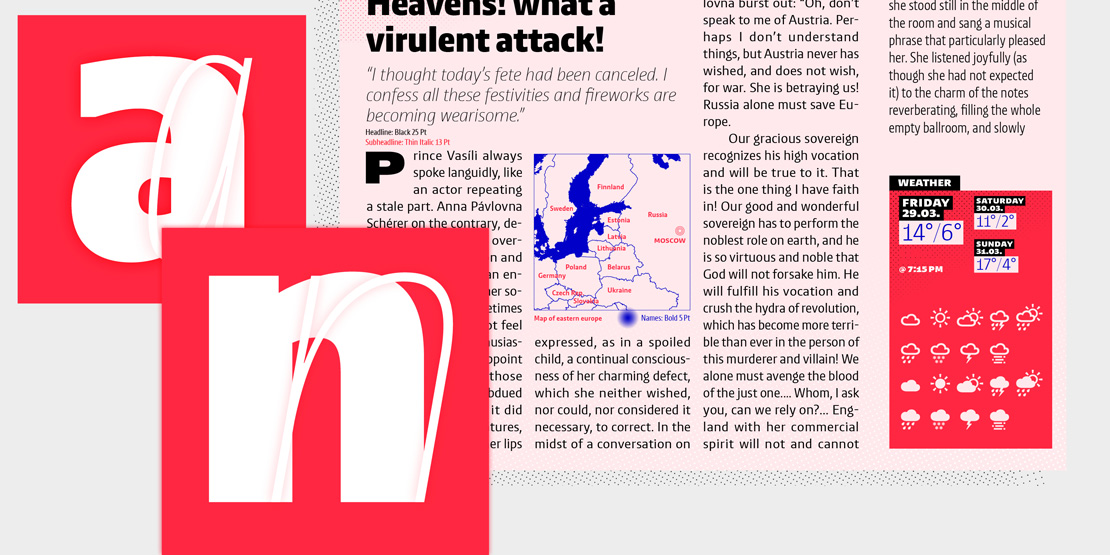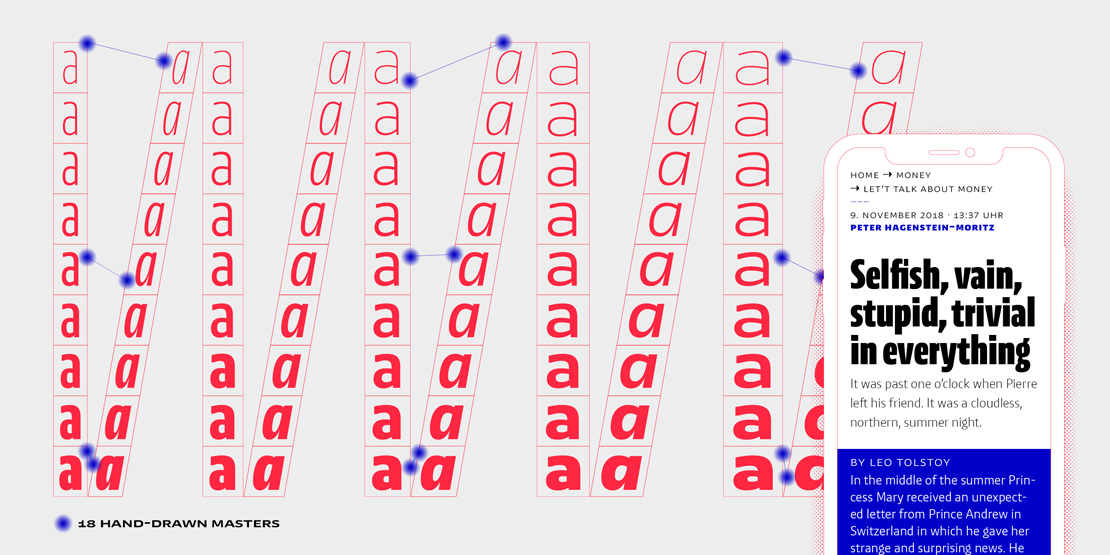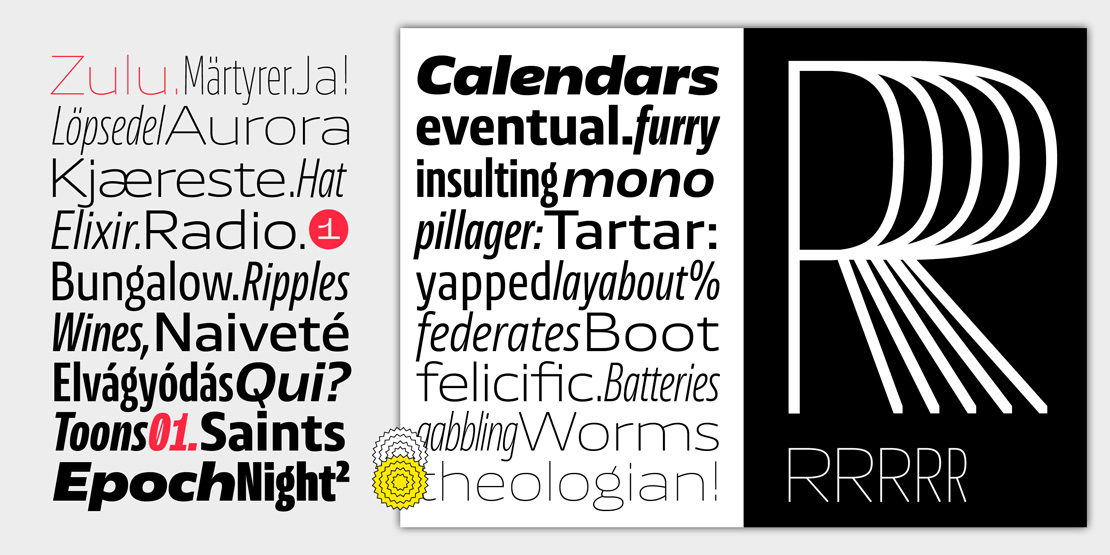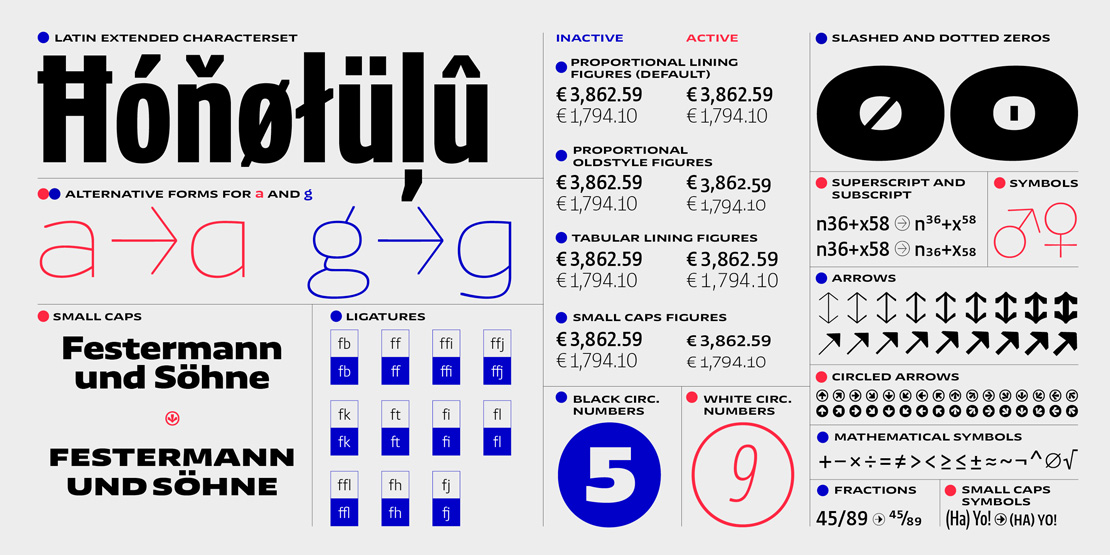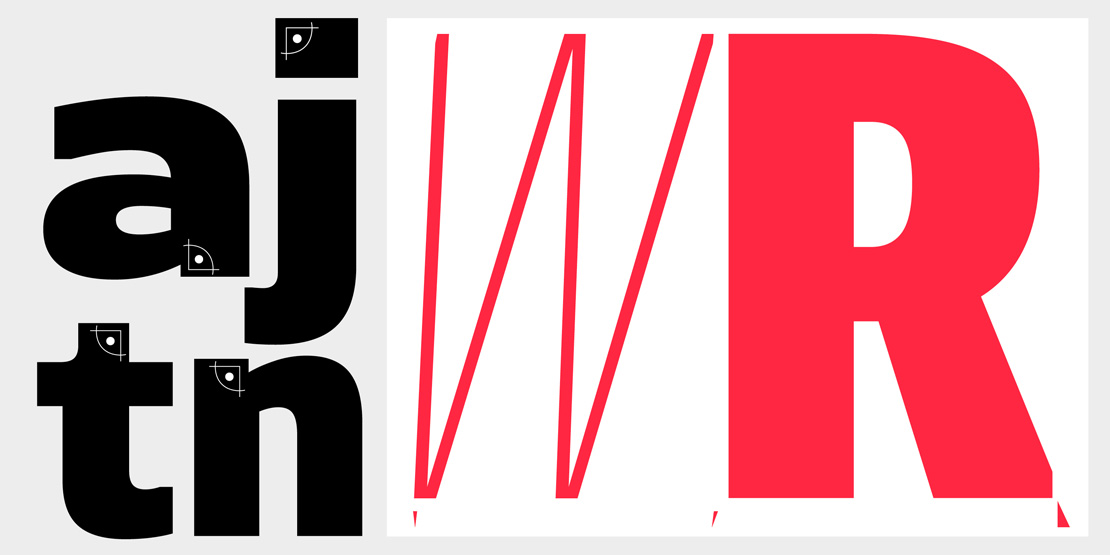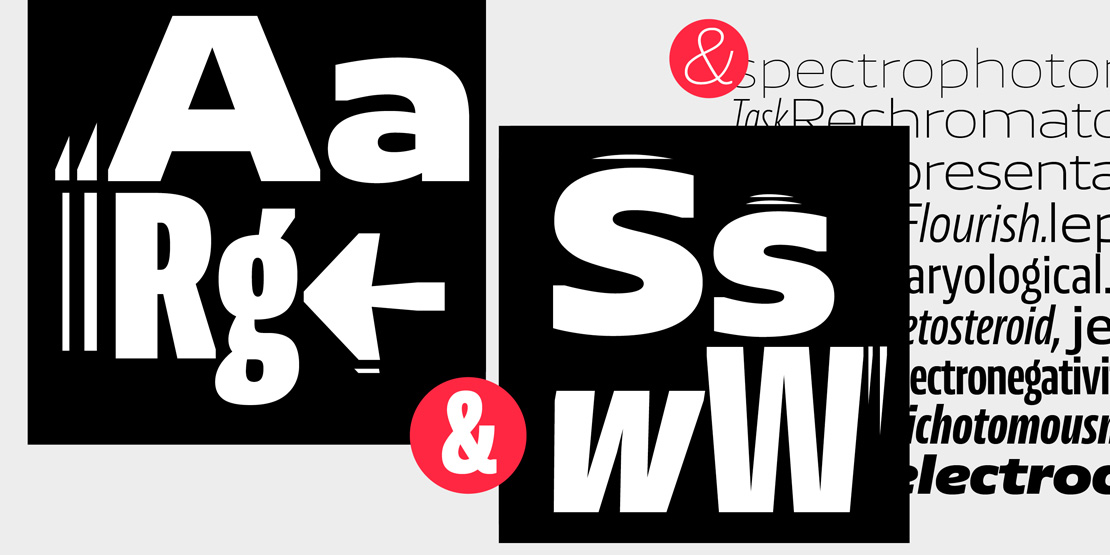
»NewsSans« in 90 Schriftschnitten von Character Type
Character Type veröffentlicht die Schrift »NewsSans« als Superfamilie in 90 Schnitten. Begleitet wird sie durch das Magazin »characters#01«, das Typomagazin und Schriftmuster zugleich ist.
Die Schrift »NewsSans« ist ein typografisches Allzweckwerkzeug mit 90 Schnitten. Sie steht zudem für typografische Vielschichtigkeit. Durch die Vielfalt an Fonts lässt sich beispielsweise von laut und ausdrucksstark bis hin zu feingliedrig und zurückhaltend variieren.
Schrift mit Charakter
Die große x-Höhe in Kombination mit kurzen Ober- und Unterlängen ermöglicht platzsparenden und effizienten Satz. »NewsSans« hat keine spitz nach außen gerichteten Ecken. Dadurch kann Platz gespart und der Schrift ein Stück extra Charakter verliehen werden.
Der allgemein humanistische Duktus wurde durch einige »American Grotesk«-Details angereichert und durch absolut gerade Abstriche gekontert.
Variantenreiche NewsSans
Die Superfamilie hat neun Strichstärken von »Hairline« bis »Black« in jeweils fünf Breiten von Compressed bis Extended, jeweils mit einer echten Italic. »NewsSans« wurde durch manuelles Hinting für die Darstellung auf Displays optimiert. Jeder Font enthält außerdem über 700 Zeichen und OpenType-Features für Kapitälchen, Mediävalziffern, Tabellenziffern, Kapitälchenziffern, Ligaturen und Alternativbuchstaben.
characters#01 – Typomagazin und Schriftmuster
Ergänzend zur »NewsSans« ist mit characters#01 eine Mischung aus Typomagazin und Schriftmuster erscheinen. Die erste Ausgabe enthält ein Interview mit dem Erfinder digitaler Schrift Peter Karow, einen Essay über Charakter in Schrift und eine Auswahl an traditionellen polnischen Scherenschnitten. Und natürlich wird auch die »NewsSans« gezeigt. characters#01 ist im slanted shop erhältlich.